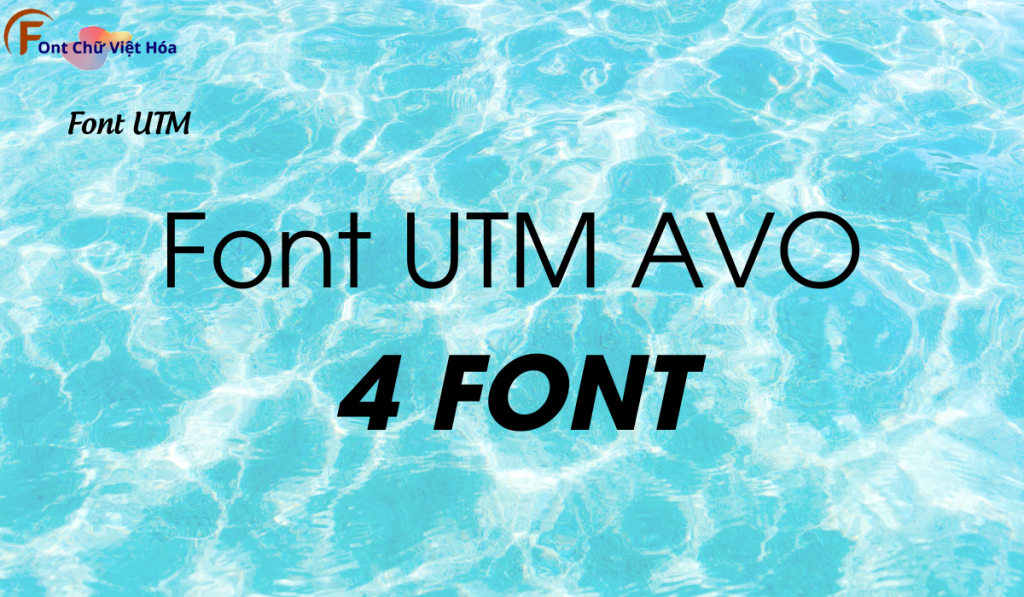
Font UTM Avo Việt Hóa
Kiểu chữ: Sans-serif
Độ dày: Regular, Bold, Italic, Bold Italic
Font UTM Avo Việt Hóa là một font chữ không chân hiện đại, thuộc bộ font UTM. Được thiết kế với mục tiêu mang lại sự đơn giản và hiệu quả, font này lý tưởng cho các dự án thiết kế như giao diện người dùng, ứng dụng di động, và website. Với các nét chữ rõ ràng và độ dày đều đặn, Font UTM Avo Việt Hóa không chỉ dễ đọc mà còn tạo cảm giác hiện đại và chuyên nghiệp. Việc Việt hóa font giúp người dùng dễ dàng tích hợp vào các thiết kế tiếng Việt, mang lại sự tiện lợi và nâng cao tính thẩm mỹ.